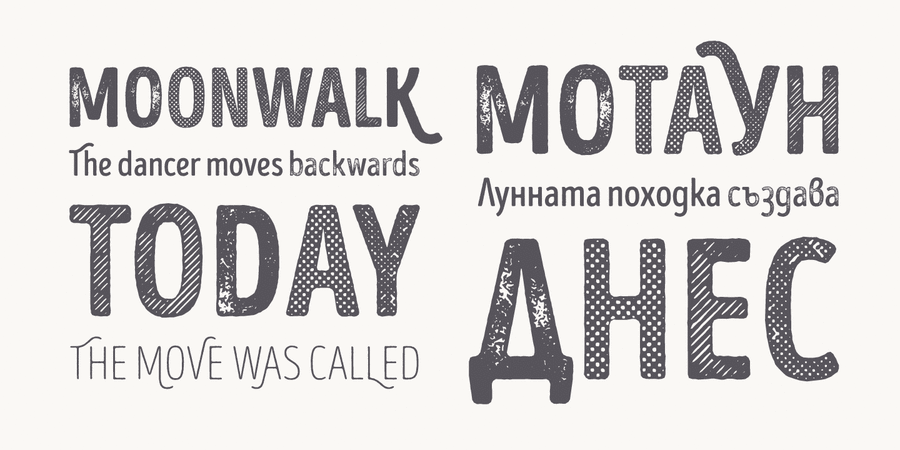
Intro Head R Base (1 шрифт)
Бесплатное начертание одной из крупнейших шрифтовых систем в мире Интро Раст, включающей 214 начертаний. Это огрубленная текстурная версия известного шрифта Интро. Система Интро Раст включает 4 семейства: Intro Rust, Intro Script, Intro Head и Intro Goodies. Она может применяться для создания почти всех видов дизайнерской продукции от полиграфии до веб-дизайна. Просто используйте воображение и ваши проекты станут более живыми, благодаря шрифтам системы Интро Раст. Хотите сделать поздравительную открытку или дизайн упаковки или даже айдентику? Смело экспериментируйте с паттернами и рисунками, рукописными версиями или теми классными начертаниями с точками и получайте современный успешный дизайнерский проект. Шрифт разработан Светославом Симовым, Ани Петровой и Радомиром Тинковым в 2015 году и выпущен фирмой Фонтфабрик. http://www.fontfabric.com/intro-rust/
Асоціації з сімейством шрифтів Intro Head R BaseОсобистість і характер гарнітури:
чесний, добрий, М'який, відкритий, Простий, екологічний, доброзичливий, довірчий, натуральний, свіжий, акуратний, спокійний, рівний, універсальний, зрозумілий, врівноважений, ненав'язливий, помірний, прямий, сучасний, непомітний, практичний, лаконічний, доступний, комфортний, приємний, гармонійний, міський, здоровий, стрункий, весняний, органічний, природний, мирний
— Гарнітура асоціюється з віком: